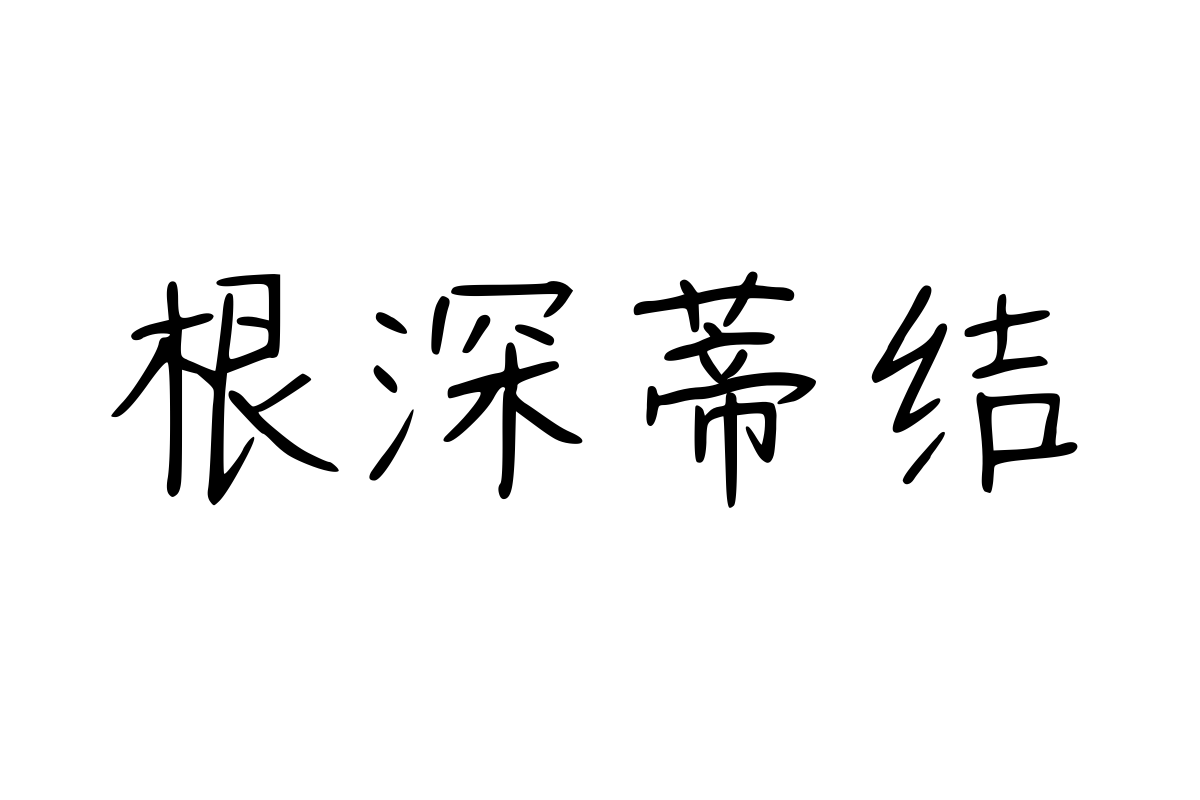
思雨不问归期是一款现代简约风格的中文字体,具有独特的艺术风格和强烈的视觉冲击力。这款字体采用了简洁的线条和清晰的结构,使得整个字体看起来既优雅又有力。
该字体适用于各种设计场景,如广告、海报、网页设计等。它不仅适合用于商业品牌宣传,也适合用于个人作品展示或社交媒体内容创作。
思雨不问归期的字体特点包括:
– 简洁的线条和清晰的结构,使得整个字体看起来既优雅又有力。
– 适合用于各种设计场景,如广告、海报、网页设计等。
– 适合用于商业品牌宣传,也适合用于个人作品展示或社交媒体内容创作。
思雨不问归期